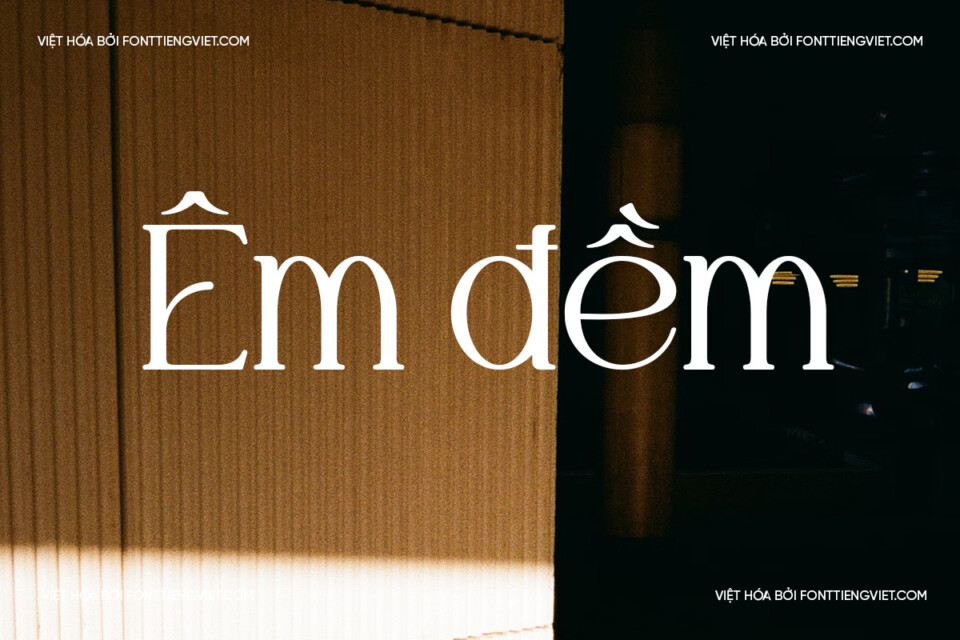
Font Việt hóa 1FTV VIP MOELA
Font Việt hóa 1FTV VIP MOELA – Bộ Font Chữ Nghệ Thuật Đẳng Cấp Cho Thiết Kế Việt
Giới thiệu về bộ Font Việt hóa 1FTV VIP MOELA
Trong thế giới thiết kế đồ họa hiện đại, việc lựa chọn một bộ Font Miễn Phí chất lượng luôn là ưu tiên hàng đầu của các nhà sáng tạo. Font Việt hóa 1FTV VIP MOELA nổi lên như một giải pháp hoàn hảo, kết hợp giữa sự sang trọng cổ điển và hơi thở đương đại. Đây là bộ font được tinh chỉnh kỹ lưỡng về dấu tiếng Việt, giúp người dùng không còn lo lắng về lỗi hiển thị khi soạn thảo nội dung. Với những đường nét thanh mảnh nhưng chắc chắn, bộ font này mang đến một diện mạo hoàn toàn mới cho các ấn phẩm truyền thông, từ biểu ngữ trường học đến các dự án thiết kế chuyên nghiệp.
Những đặc điểm nổi bật của Font Việt hóa 1FTV VIP MOELA
Thiết kế tinh tế và chuyên nghiệp
Điểm thu hút nhất của Font Việt hóa 1FTV VIP MOELA chính là cấu trúc chữ cái cân đối và hài hòa. Từng đường cong được chăm chút tỉ mỉ, tạo nên cảm giác uyển chuyển và dễ nhìn. Đối với các bạn học sinh hay giáo viên đang tìm kiếm sự mới mẻ cho bài giảng điện tử hoặc báo tường, bộ font này cung cấp một phong cách thẩm mỹ rất cao mà vẫn đảm bảo tính trang trọng cần thiết cho môi trường sư phạm.
Khả năng ứng dụng đa dạng trong thực tế
Không chỉ giới hạn trong trình chiếu, Font Việt hóa 1FTV VIP MOELA còn cực kỳ hiệu quả khi dùng làm tiêu đề cho các tạp chí, thiệp mời, hoặc thiết kế logo thương hiệu. Sự linh hoạt của nó cho phép người dùng kết hợp dễ dàng với nhiều loại font chữ khác để tạo ra sự tương phản ấn tượng. Đặc biệt, bộ font này hỗ trợ đầy đủ các ký tự đặc biệt, giúp việc sáng tạo nội dung tiếng Việt trở nên mượt mà và giàu cảm xúc hơn bao giờ hết.
Tối ưu hóa trải nghiệm người dùng Việt
Một trong những vấn đề lớn nhất khi sử dụng font ngoại quốc là lỗi dấu câu. Tuy nhiên, với phiên bản Font Việt hóa 1FTV VIP MOELA, mọi ký tự như “ă”, “â”, “đ” hay các dấu thanh đều được đặt đúng vị trí, không bị lệch hay chồng lấn. Điều này không chỉ giúp bản thiết kế trông chuyên nghiệp hơn mà còn giúp người xem dễ dàng tiếp nhận thông tin mà không bị gây nhiễu bởi các lỗi kỹ thuật không đáng có.
Hướng dẫn sử dụng Font Việt hóa 1FTV VIP MOELA hiệu quả
Để phát huy tối đa vẻ đẹp của Font Việt hóa 1FTV VIP MOELA, bạn nên chú ý đến khoảng cách giữa các chữ cái (kerning) và dòng (leading). Trong các thiết kế tối giản, hãy thử để bộ font này làm điểm nhấn duy nhất trên phông nền đơn sắc, bạn sẽ thấy sự khác biệt rõ rệt. Ngoài ra, việc sử dụng các định dạng in đậm hoặc in nghiêng của font cũng giúp tạo ra hệ thống phân cấp thông tin rõ ràng, giúp người đọc nắm bắt nội dung nhanh chóng hơn.
Kết luận về bộ Font Việt hóa 1FTV VIP MOELA